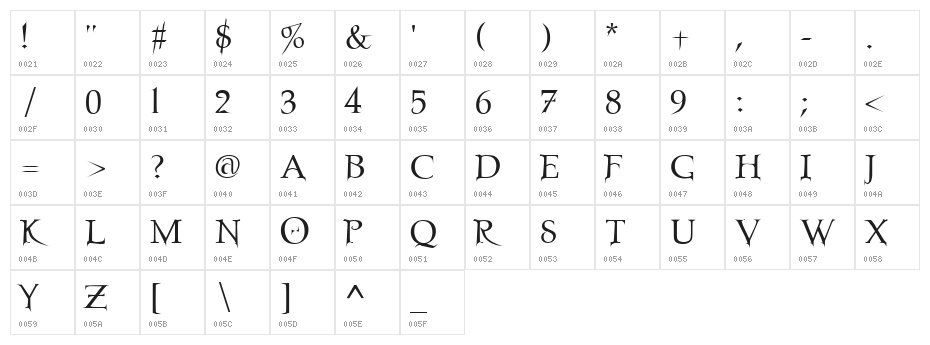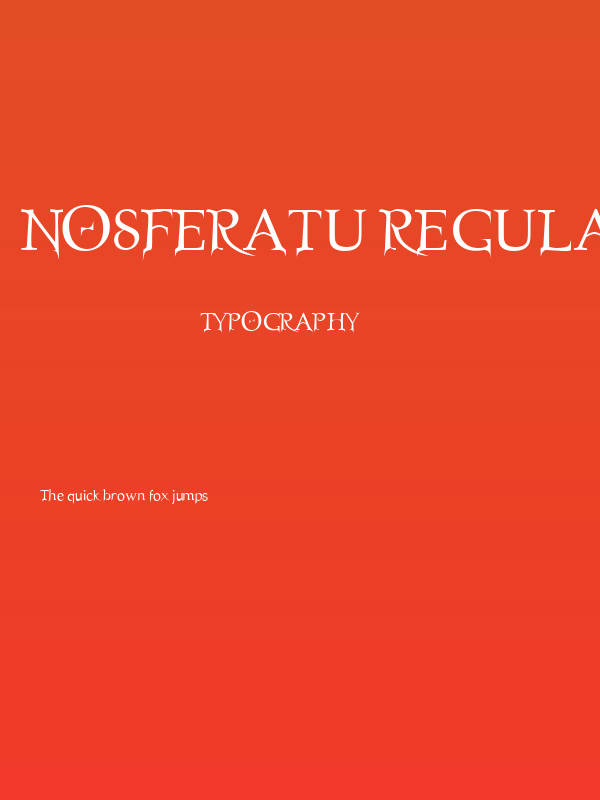
Nosferatu Regular Font
| Gesamtstil | Gothic, Dramatic |
| Vorgeschlagene Projekte | Ideal for horror-themed posters, book covers, movie titles, and Halloween event invitations. |